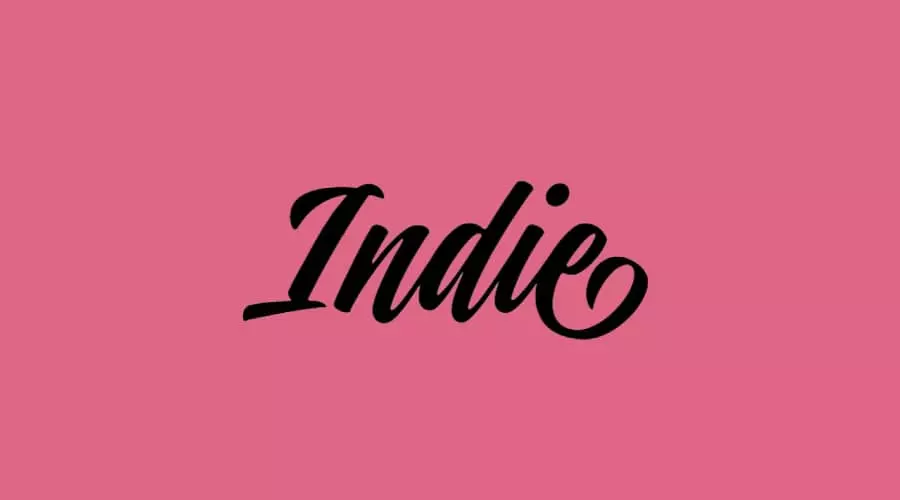
Tác giả: Maximiliano Sproviero
Phân loại: Cá tính
Font SVN Indie là một trong những phông chữ thuộc bộ font SVN độc đáo và sáng tạo được nhiều người thiết kế và nhà sáng tạo nội dung ưa chuộng. Với phong cách trẻ trung, phóng khoáng, font SVN Indie không chỉ mang lại cảm giác mới mẻ mà còn giúp truyền tải thông điệp một cách rõ ràng và thu hút. Được sử dụng rộng rãi trong các dự án thiết kế logo, banner và ấn phẩm truyền thông, font này đóng vai trò quan trọng trong việc xây dựng thương hiệu và tạo ấn tượng mạnh mẽ. Nếu bạn đang tìm kiếm một kiểu chữ vừa phá cách vừa chuyên nghiệp, font SVN Indie chắc chắn là lựa chọn không thể bỏ qua.